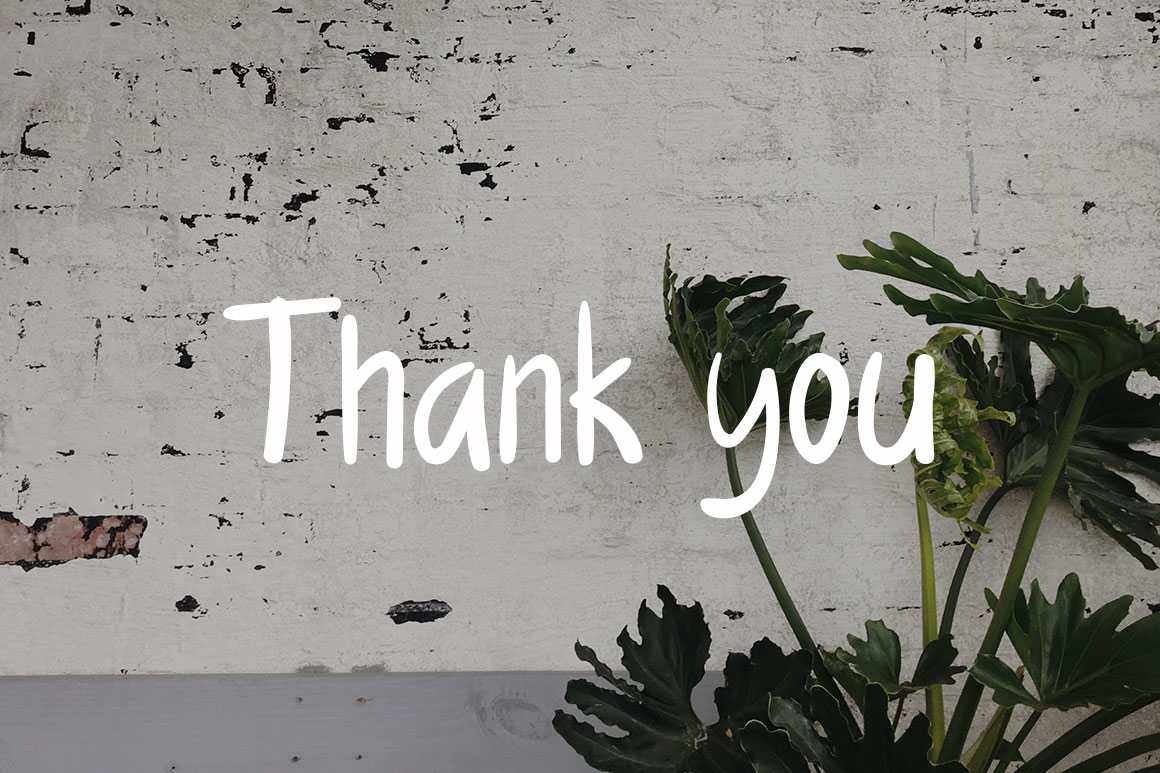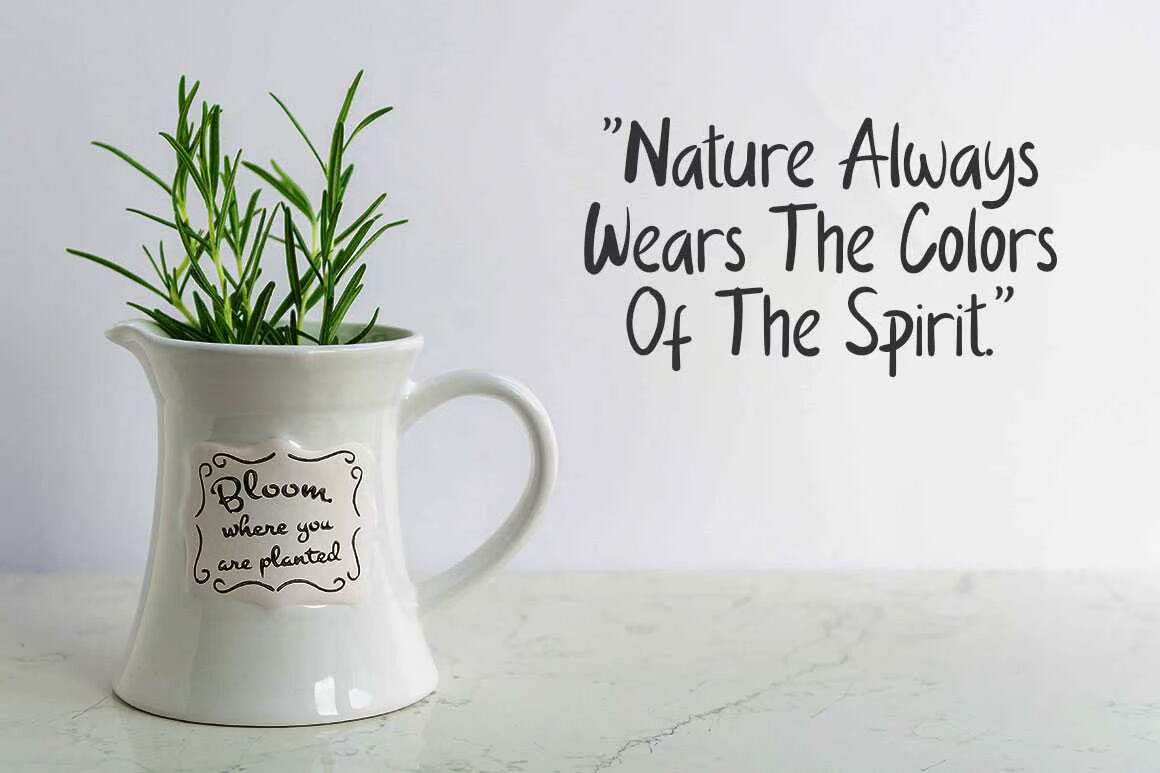
Nuanzaisa和Lettered Condensed Ansser致力于通过一个内置的IP Penture实现个性化触控。它适用于品牌项目、徽标、婚礼设计、社交媒体、广告、产品包装、产品设计、标签、摄影、水印、邀请函、文具、,以及任何其他需要书写和粘贴的项目。Nuanzaisa和Lettered CondensedAnsser通过一个不可复制的文本来实现个性化触感。它适用于品牌项目、徽标、婚礼设计、社交媒体、广告、产品包装、产品设计、标签、摄影、水印、邀请函、文具、,以及任何其他需要手动写入的项目。